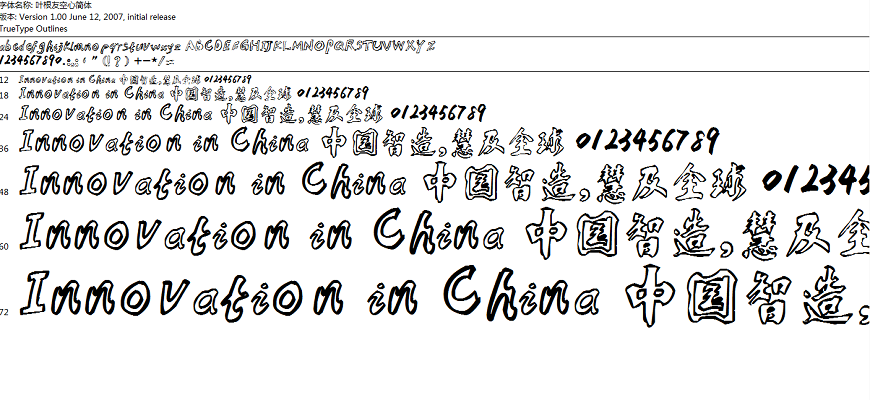
葉根友空心簡體是一款特意為紀(jì)念香港回歸十周年所發(fā)布的書法字體,字體內(nèi)部全部鏤空,卻不會(huì)讓人覺得字體沒有骨干,反而給人一種別樣的立體感,非常的與眾不同,感興趣的朋友們快來下載吧!
葉根友空心簡體是由中國書法奇人葉根友先生書寫,并在香港回歸十周年之際正式發(fā)布。 字體清晰自然,實(shí)用性強(qiáng),是書寫信件,BLOG等個(gè)性化字體的一不錯(cuò)的選擇.